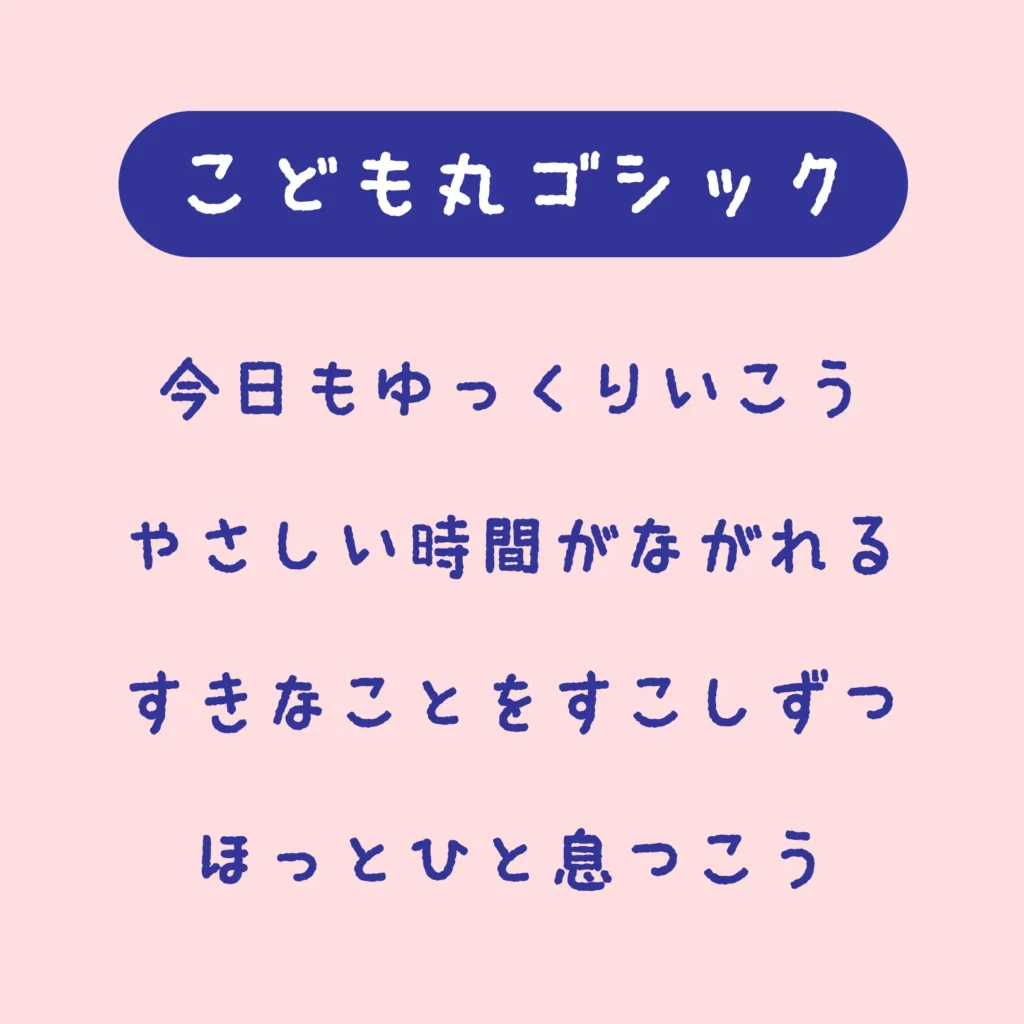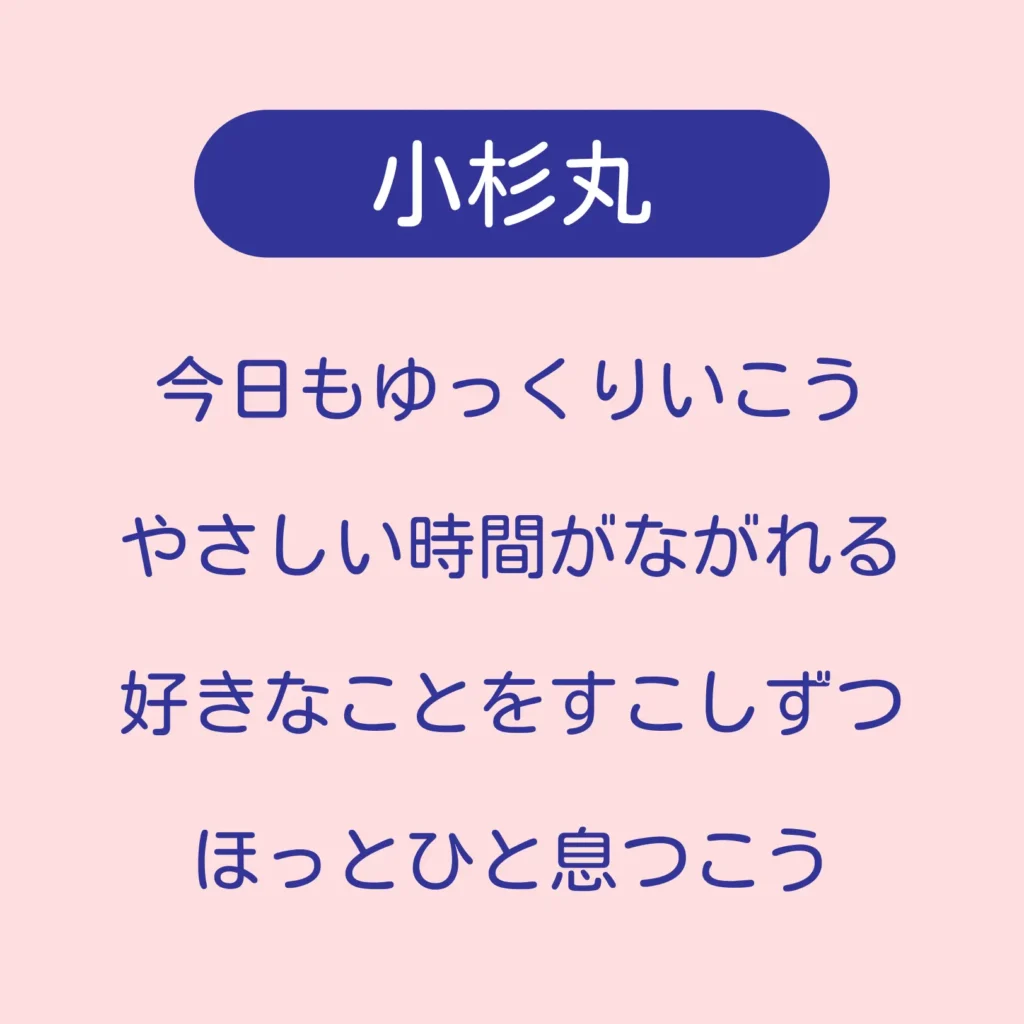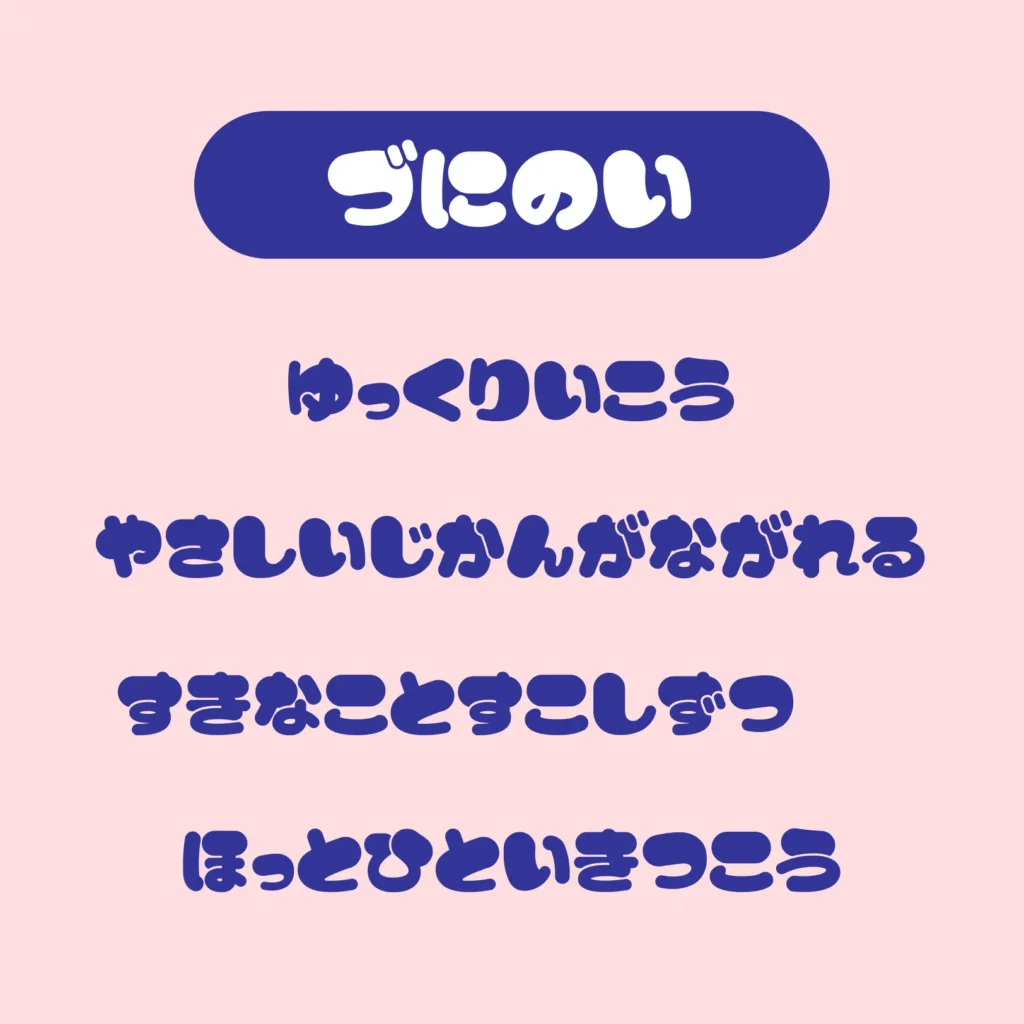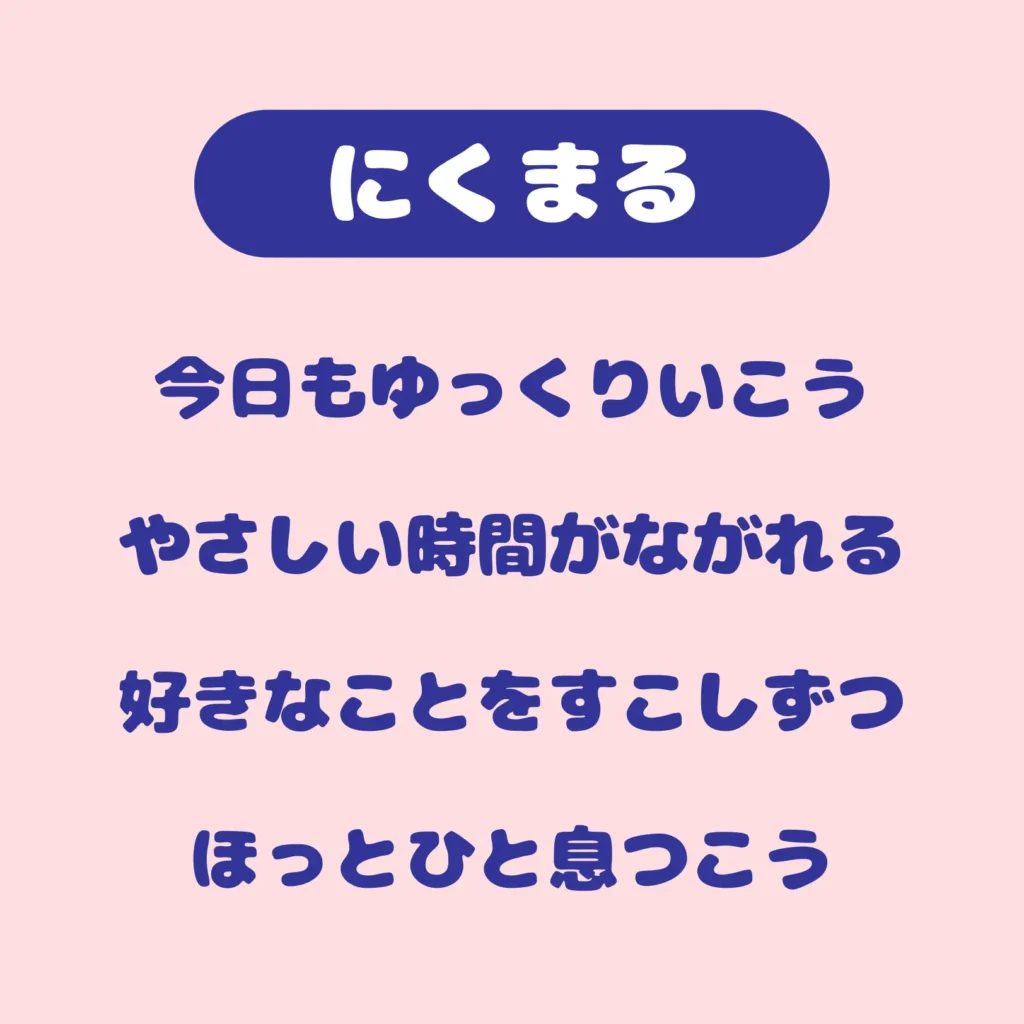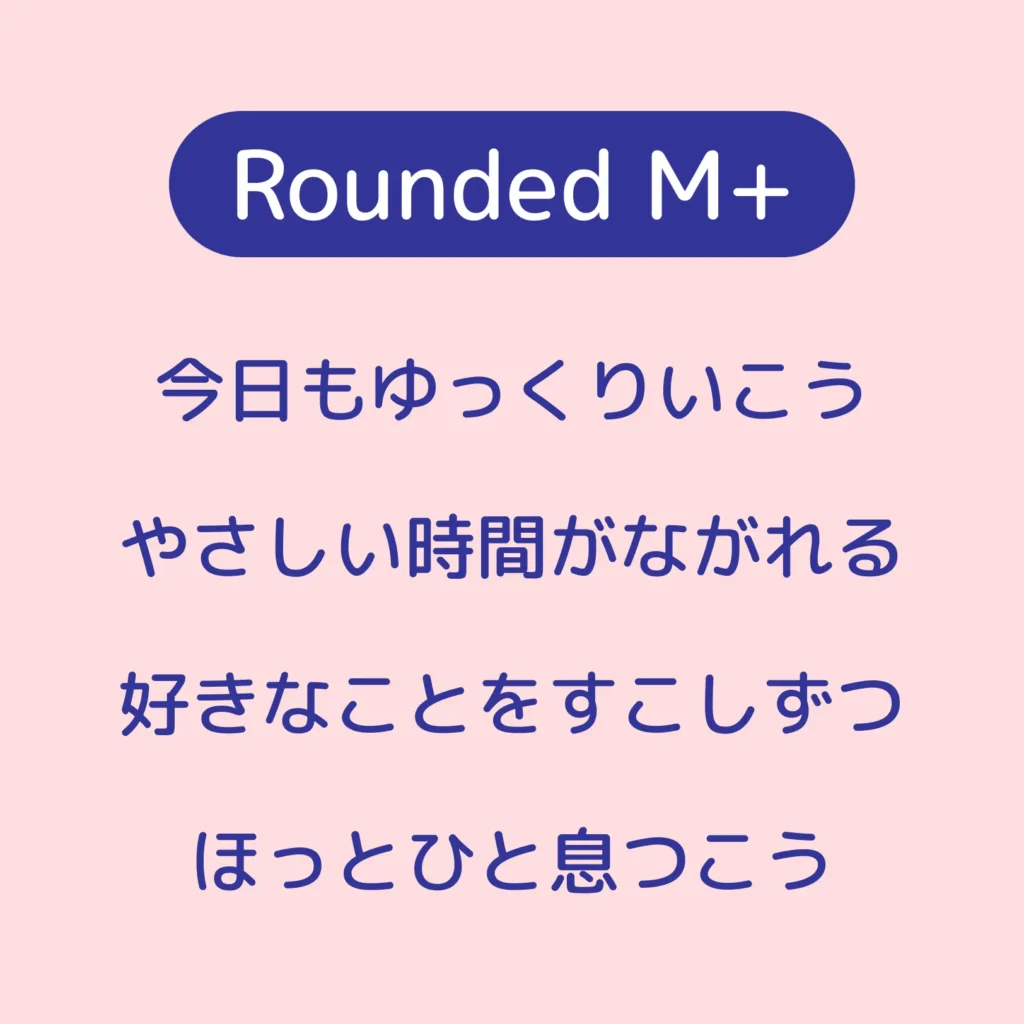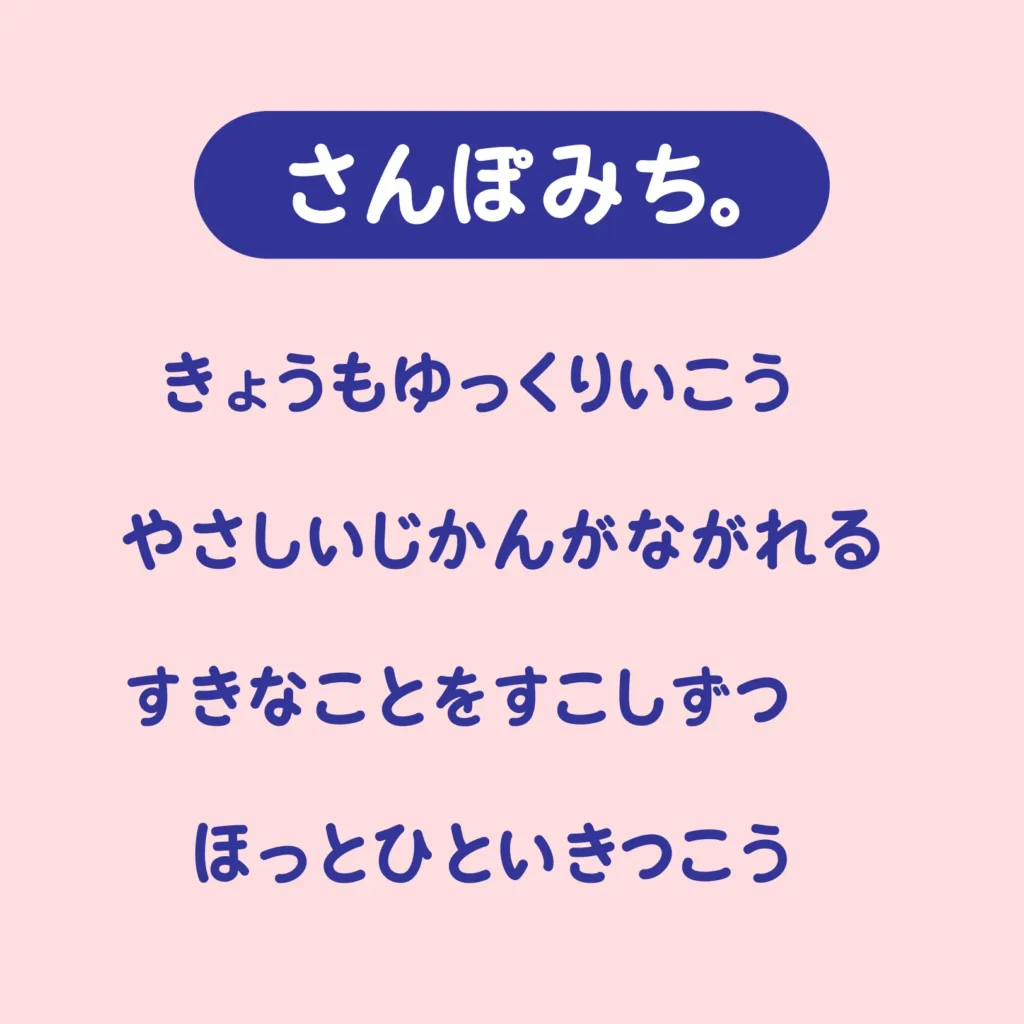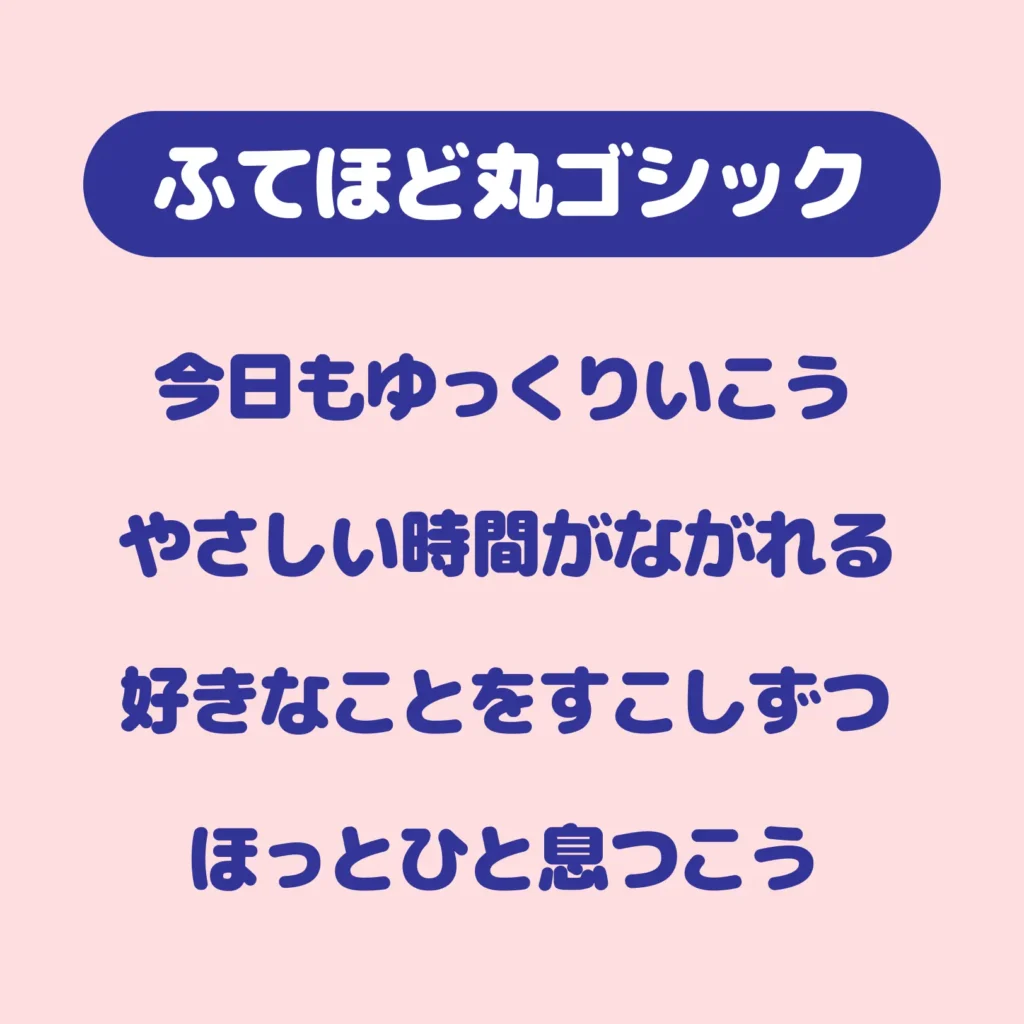
「丸文字」フリーフォントをご紹介!
やさしく丸みのある文字は、デザインに親しみやすさや柔らかな印象を与えてくれます。
太すぎず細すぎないラインや、コロンとしたフォルムは、可愛さと読みやすさのバランスがよく、さまざまな場面で使いやすいのが特徴です。
丸文字のおすすめフリーフォントの一覧
・遠くからでも認識しやすい
・かわいさがありつつ甘くなりすぎない
・短い言葉から文章まで扱いやすい
といった点を基準に厳選したフォントたちです。
「やさしい雰囲気のデザインに仕上げたい」
「読みやすさと可愛さを両立させたい」
そんな方に向けて、丸文字フォント選びのヒントとして、ぜひ参考にしてみてください。。
1.小杉丸
小杉丸
視認性⭐⭐⭐⭐☆
うちわ向き⭐⭐⭐⭐☆
使用用途Web本文/パンフレット/UIデザイン
癖のない丸ゴシック体で、全体のバランスがよく非常に読みやすいフォント。主張しすぎない丸みがあり、文字数が多くても安定した印象に仕上がります。
2. Rounded M+
Rounded-M+
視認性⭐⭐⭐⭐☆
うちわ向き⭐⭐☆☆☆
使用用途サムネイル/見出し/Web制作
整った字形と高い可読性が特徴の丸文字ゴシック。シンプルながら洗練された印象で、情報を正確に伝えたい場面にも安心して使えます。
3. にくまる
にくまる
視認性⭐⭐⭐☆☆
うちわ向き⭐⭐⭐⭐⭐
使用用途ロゴ制作/アイキャッチ/SNS投稿
文字全体がふっくらと丸く、ひと目で可愛さが伝わるフォント。やや太めの線で存在感があり、短い言葉でも印象に残りやすいのが魅力です。
4. Mike(づにのい)
づにのい
視認性⭐⭐☆☆☆
うちわ向き⭐⭐⭐⭐☆
使用用途サムネイル/タイトル文字/推し活デザイン
独特の丸みと個性的な字形が印象的なフォント。文字そのものにキャラクター性があり、他と差をつけたいデザインに使いやすい書体です。
5. ふてほど丸ゴシック
ふてほど丸ゴシック
視認性⭐⭐⭐☆☆
うちわ向き⭐⭐⭐⭐⭐
使用用途見出し/告知デザイン/グラフィック制作
太めで安定感のある線と丸みが特徴の丸ゴシック体。力強さと読みやすさを兼ね備え、視線をしっかり引きつけます。
6. こども丸ゴシック
こども丸ゴシック
視認性⭐⭐☆☆☆
うちわ向き⭐⭐☆☆☆
使用用途教材制作/イラスト/やさしいデザイン
やわらかく素直な字形で、安心感のある丸文字フォント。角のないデザインがやさしい印象を与え、幅広い年代に馴染みます。
7. はちまるポップ
はちまるポップ
視認性⭐⭐☆☆☆
目立ち度⭐⭐⭐⭐☆
使用用途イベント告知/SNS画像/クリエイター投稿
元気でポップな雰囲気の丸文字フォント。リズム感のある字形で、楽しさや明るさを前面に出したいデザインに適しています。
8. さんぽみち。
さんぽみち。
視認性⭐⭐☆☆☆
目立ち度⭐⭐☆☆☆
使用用途SNS投稿/イラスト文字/創作作品
手描き風のやさしい丸文字が特徴で、ほんわかとした温かみを感じるフォント。柔らかく親しみやすい雰囲気を演出したいときに向いています。
まとめ